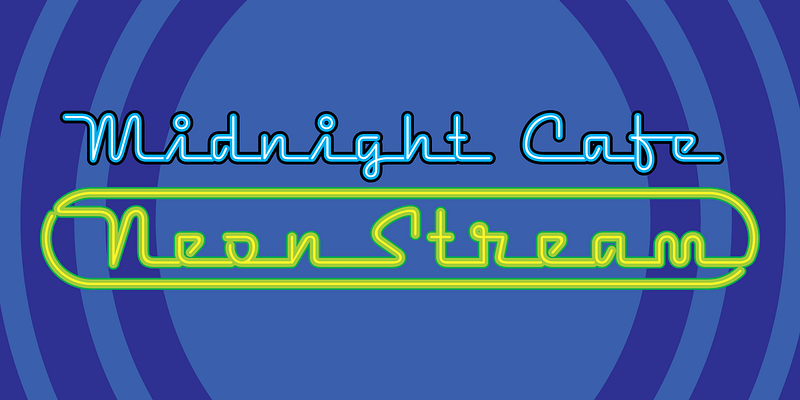
Le scintillement froid des enseignes écrites en lettres aux couleurs artificielles rappellera toujours les bars, les restaurants, les débits de bière, les chaînes de hot-dogs, les casinos sur le Las Vegas Strip, bref, le royaume de l’éclairage au néon. Les tubes de verre cintrés remplis de gaz lumineux donnent la forme si familière de ces caractères rétro ; la graisse uniforme des caractères et les courbes délibérées offrent une combinaison inhabituelle avec des couleurs extravagantes et provocantes pour évoquer les folles nuits de Las Vegas ; FB 1995
Zavier Cabarga a dessiné des images et des caractères toute sa vie. « Le dessin exige une perception inhérente de l’anatomie et de la proportion. Il en va de même pour la typographie, car je crois que nos anciennes lettres sont basées sur les proportions humaines », explique Zavier. « C’est d’abord les bandes dessinées qui m’ont inspiré, puis j’ai commencé à copier des logos et des caractères de titrage que je trouvais dans des magazines. À 15 ans, j’ai décapé des négatifs pour former une police de photocomposition brute mais utilisable. »
Travaillant sous le nom Handy Lettering Co. pendant de nombreuses années, Zavier a créé des caractères à la main pour des clients du secteur de la publicité tout en travaillant à temps plein comme illustrateur. « Dessiner des illustrations a toujours semblé difficile, alors qu’écrire, c’est facile et amusant », explique Zavier. « Je travaille depuis 25 ans sur Macintosh, ce qui m’a permis de créer des polices d’ordinateur, ce qui, à bien des égards, est la chose la plus satisfaisante que je fasse. Taper une lettre ou un caractère manuscrit avec une police que j’ai créée me donne l’impression d’être Dieu ».